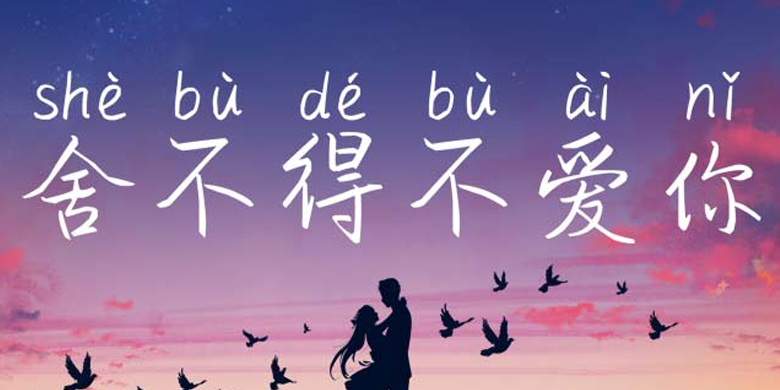
方正手迹-舍不得不爱你
字体品牌: 方正手迹 设计师:刘晔 字体分类:常规书写·硬笔 字体属性:精品字 字符集:大陆简体(GB2312-80) 发布时间: 2020
舍不得不爱你是一款添加了拼音的手写体。这款字行笔劲健爽利,抑扬顿挫,富有韵律感。中宫较为紧凑,外围舒展,整体有强烈的节奏感。适用于现代诗歌、短文的排版以及文化、商业类品牌的广告语设计。